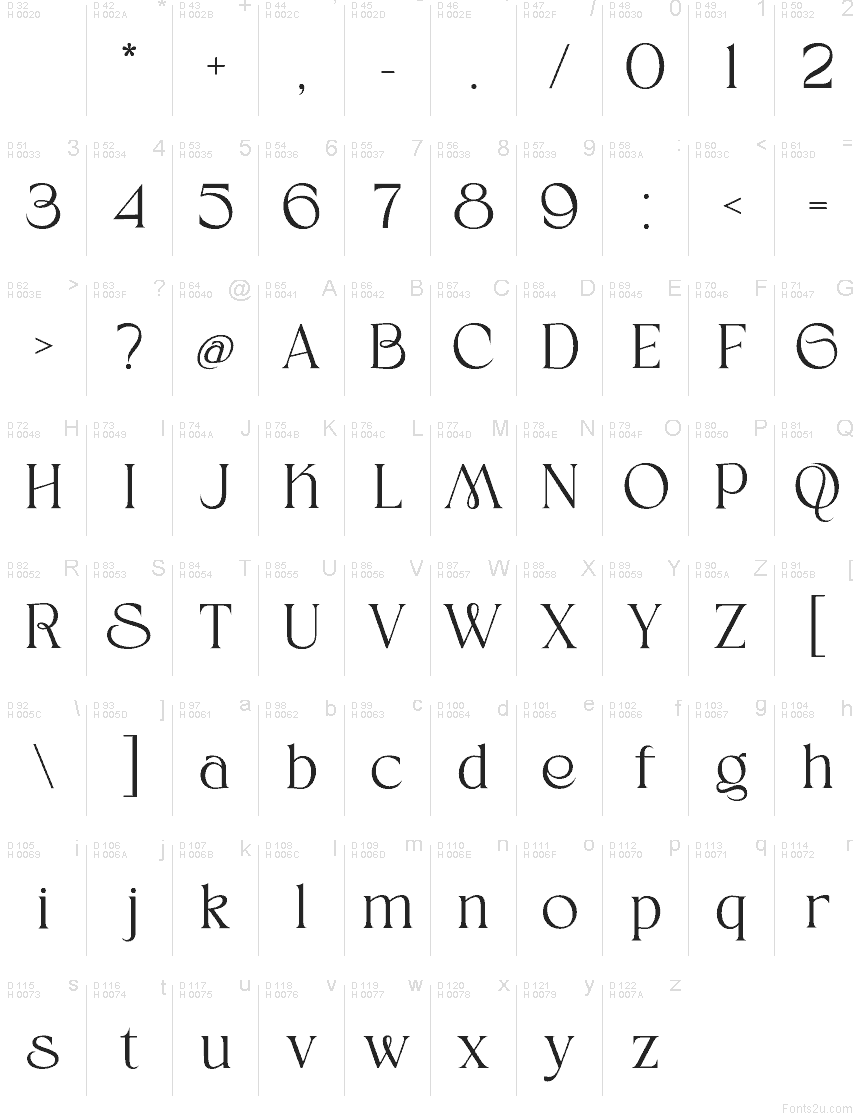
Beyline, di Afkari Studio, è un font serif gratuito ad alto contrasto con un tocco fashion e vagamente calligrafico. Le lettere abbinano tratti sottili a curve voluttuose e giunture lunghe e aggraziate, rendendo il carattere elegante ma mai rigido.
Si inserisce perfettamente nel branding beauty, nel packaging di boutique, nelle copertine di riviste, nella cartoleria per matrimoni e nei titoli dove serve un pizzico di drammaticità. Come font gratuito, Beyline è ideale per titoli brevi, loghi e monogrammi, poiché le sue curve sinuose e il contrasto marcato conferiscono una forte presenza anche a poche lettere.